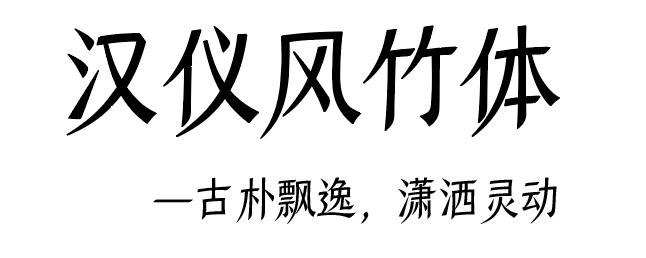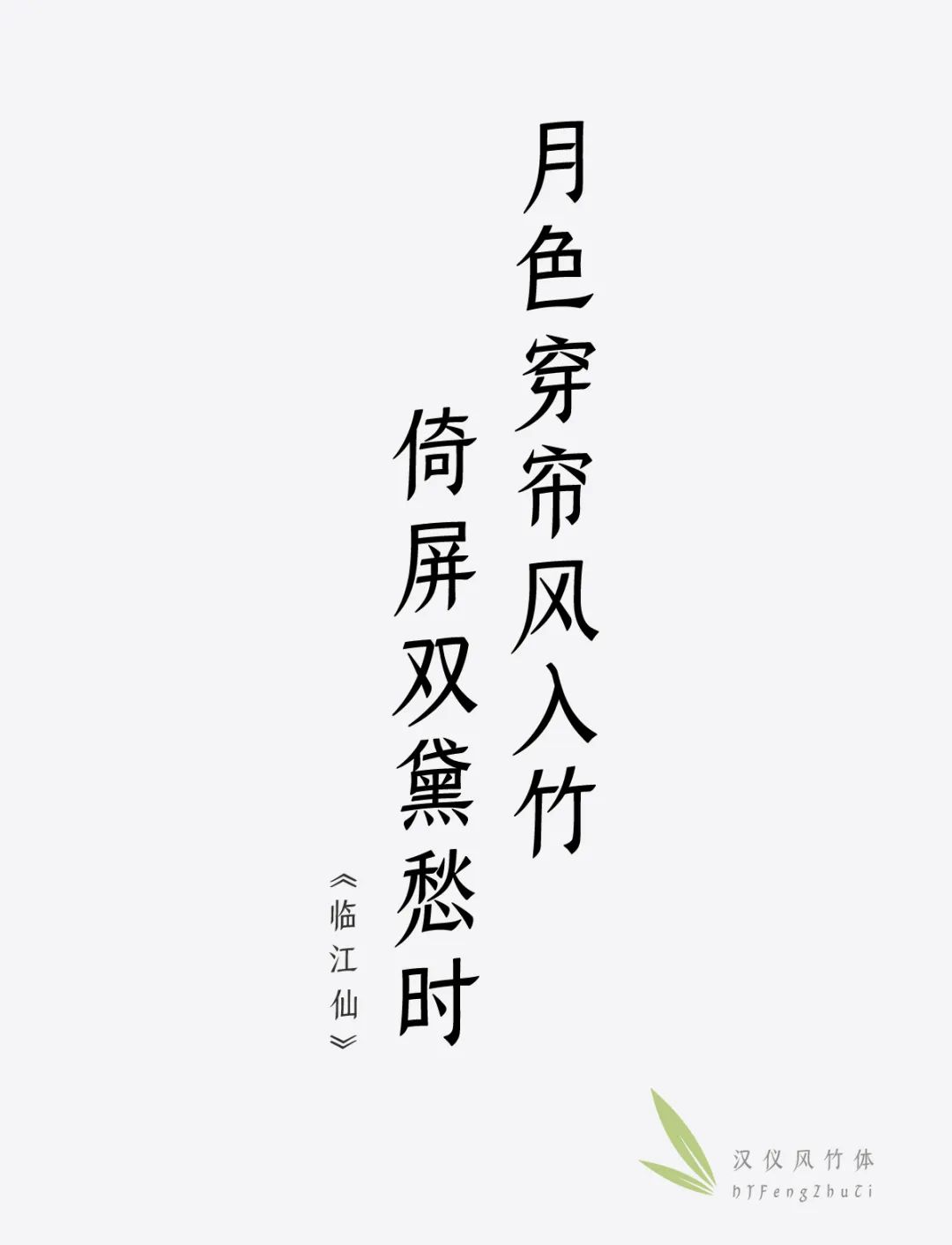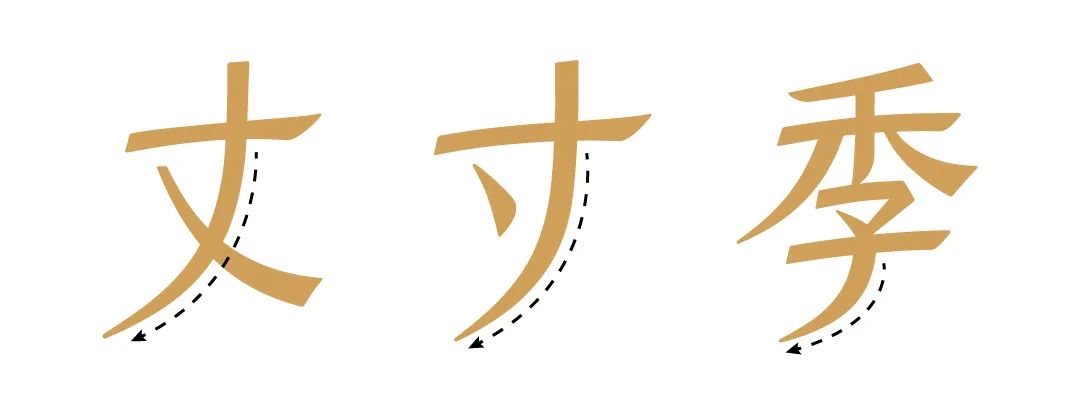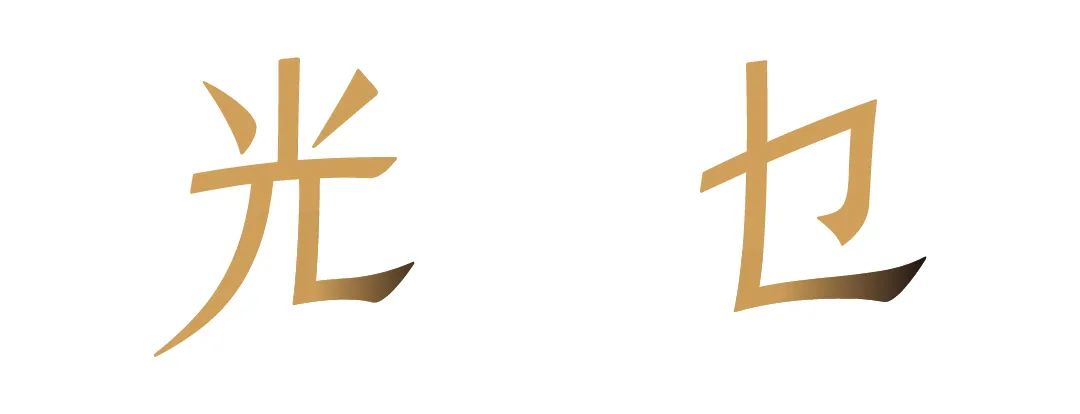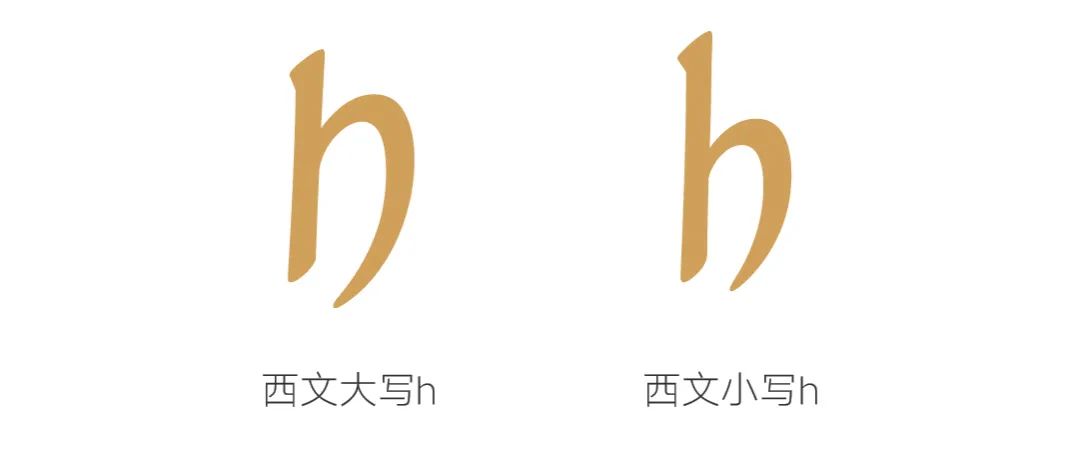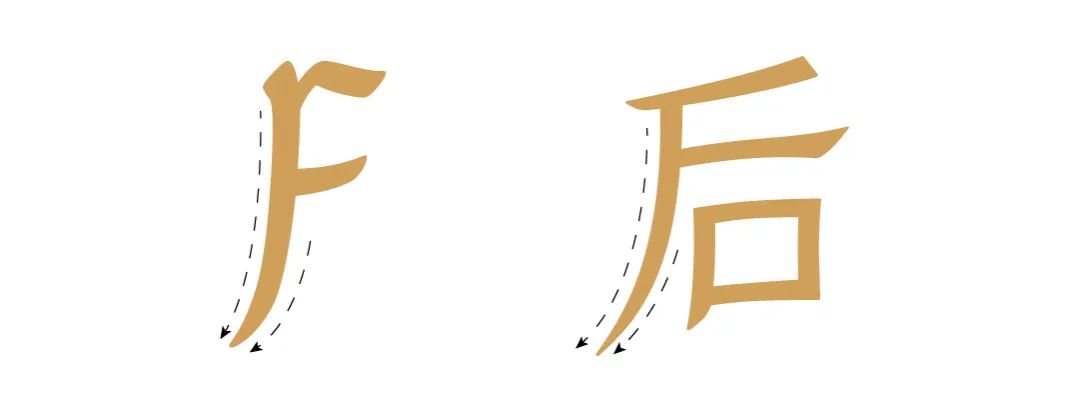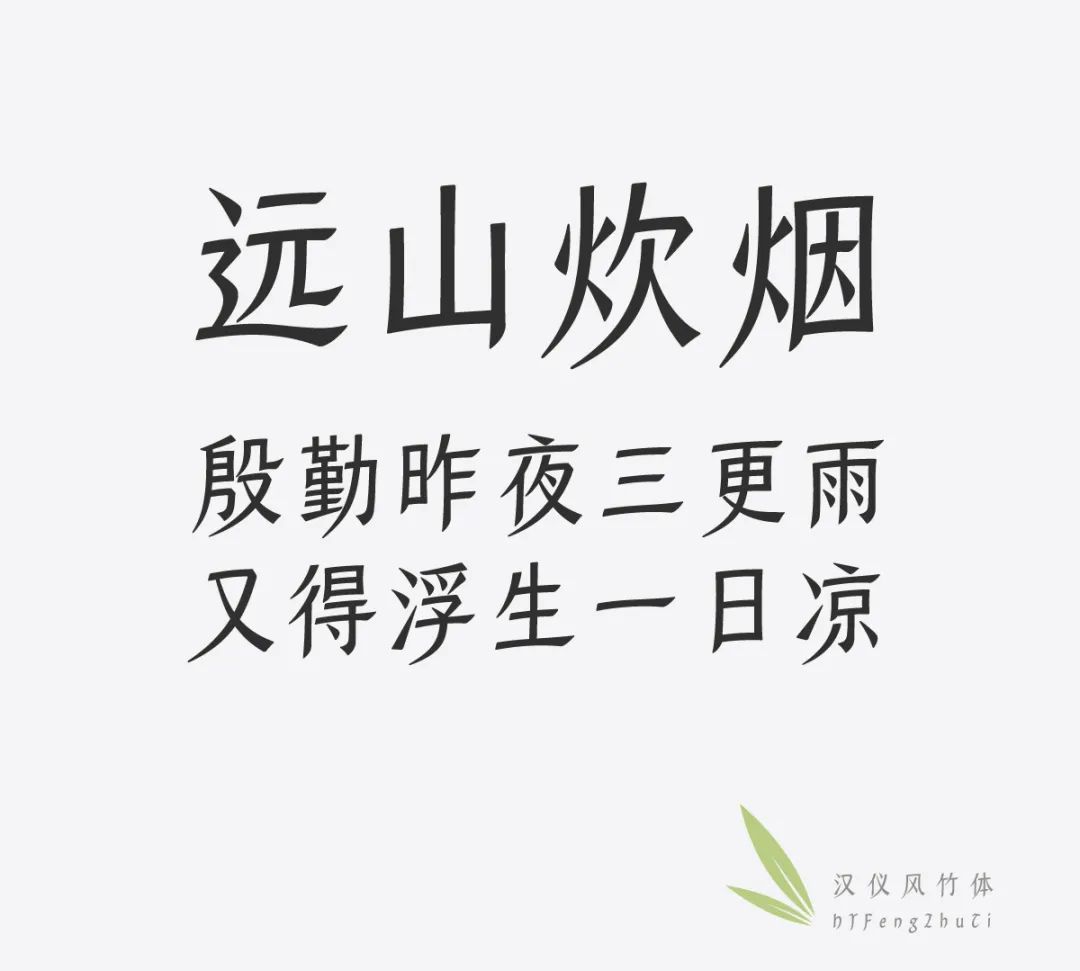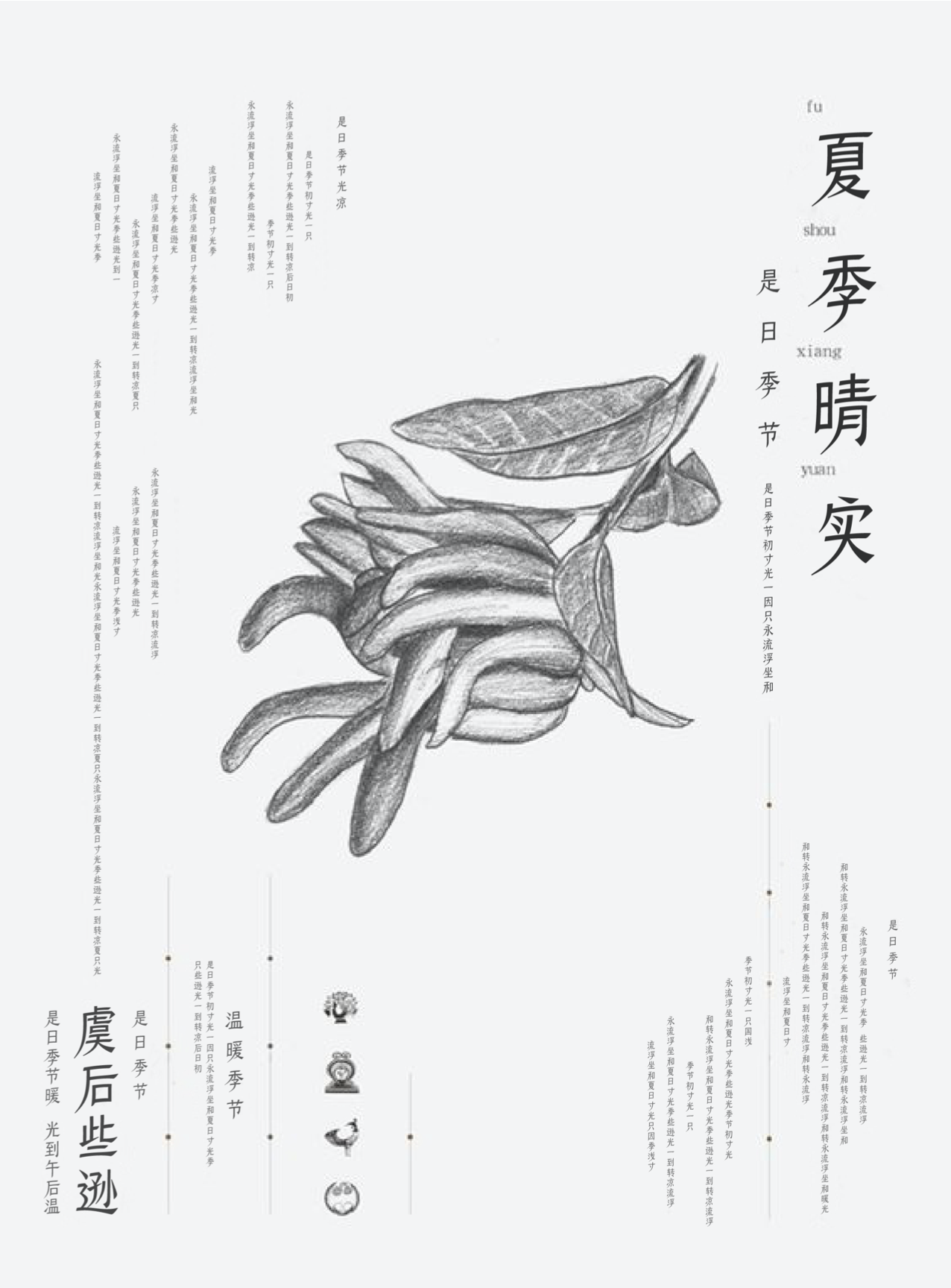
汉仪风竹体字体介绍,让古风古韵立马有了画面感~
汉仪字库设计师:罗梦怡
9169中文简繁+拉丁字符
汉仪风竹体的设计灵感来源于汉代简牍,是快写篆书向隶书转变的过渡书体。它起源于民间,用笔大胆肆意、任情恣性、不守故常、十分有趣。
汉仪风竹体的撇画是最为个性张扬的笔划,参考汉简中顺势而为的感觉,并将汉简中的夸张之笔都融入到撇画中,一些竖钩画化作撇画,更加舒展洒脱。
汉仪风竹体的钩画设计保留了由书写习惯的重顿和波磔而演化形成的雁尾形式,随势赋形这一特征的保留,使其更加舒展。
早期的拉丁字母不分大小写,最早的书体来自于人们对古罗马大写字的模仿,久而久之为了书写速度才演化出了现在大家熟知的小写形态。汉仪风竹体的西文设计保留了早期的书写风格,别具特色。
汉仪风竹体的西文字体主要以Uncial和Carolingian为主。虽然中西文两款字体的书写工具不同,字型不同,但是仔细对比后,却有许多相似的形态和感觉,这也是汉仪风竹体在做中西文匹配中最有趣的地方。